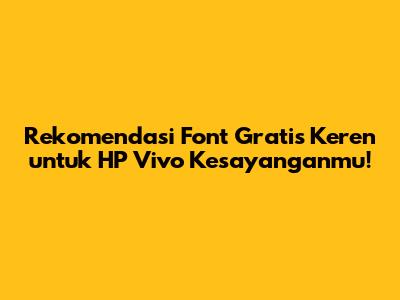
- Coba Berbagai Kombinasi: Jangan ragu untuk mencoba berbagai kombinasi font untuk menemukan tampilan yang paling cocok untuk HP kalian. Kalian bisa menggabungkan font yang berbeda untuk judul, subjudul, dan teks isi.
Hai guys! Siapa di sini yang suka banget gonta-ganti tampilan HP, khususnya font? Pasti seru banget ya rasanya kalau kita bisa mengubah-ubah font di HP Vivo kesayangan kita. Nah, buat kalian yang lagi nyari rekomendasi font gratis dan keren untuk HP Vivo, pas banget nih! Di artikel ini, kita bakal bahas tuntas tentang font-font kece yang bisa kalian unduh dan pasang secara gratis. Dijamin, tampilan HP kalian bakal makin stylish dan beda dari yang lain!
Kenapa Sih Kita Perlu Ganti Font di HP?
Sebelum kita masuk ke rekomendasi font, ada baiknya kita bahas dulu nih, kenapa sih kita perlu ganti font di HP. Selain untuk meningkatkan tampilan visual, ganti font juga bisa memberikan beberapa keuntungan lain, lho. Pertama, dengan mengganti font, kita bisa menyesuaikan tampilan HP sesuai dengan kepribadian dan selera kita. Misalnya, kalau kalian suka tampilan yang elegan, kalian bisa memilih font serif yang klasik. Atau, kalau kalian lebih suka tampilan yang kasual dan modern, kalian bisa memilih font sans-serif yang simpel.
Selain itu, ganti font juga bisa meningkatkan kenyamanan membaca. Beberapa font didesain khusus untuk memudahkan mata dalam membaca teks, terutama dalam jangka waktu yang lama. Ini sangat berguna, apalagi kalau kalian sering membaca artikel atau buku di HP. Dengan memilih font yang tepat, kalian bisa mengurangi kelelahan mata dan menikmati pengalaman membaca yang lebih baik. Gak cuma itu, mengganti font juga bisa bikin HP kita jadi lebih personal dan unik. Dengan memilih font yang sesuai dengan gaya hidup dan preferensi kita, kita bisa mengekspresikan diri melalui tampilan HP. Jadi, tunggu apa lagi? Yuk, mulai eksplorasi berbagai font keren dan sesuaikan tampilan HP Vivo kalian!
Rekomendasi Font Gratis Keren untuk HP Vivo
Nah, sekarang saatnya yang paling ditunggu-tunggu, yaitu rekomendasi font gratis yang bisa kalian gunakan di HP Vivo. Berikut adalah beberapa pilihan font keren yang bisa kalian coba:
1. Montserrat
Font Montserrat ini adalah font sans-serif yang sangat populer. Desainnya bersih, modern, dan mudah dibaca. Montserrat sangat cocok untuk tampilan yang minimalis dan elegan. Kalian bisa menggunakannya untuk berbagai keperluan, mulai dari tampilan antarmuka HP, pesan teks, hingga penulisan dokumen. Kelebihan lain dari Montserrat adalah ketersediaannya dalam berbagai variasi ketebalan (bold, italic, dll.), sehingga kalian bisa menyesuaikannya dengan kebutuhan.
2. Open Sans
Open Sans adalah font sans-serif lainnya yang sangat populer dan serbaguna. Font ini didesain oleh Steve Matteson dan telah menjadi salah satu font Google yang paling banyak digunakan. Open Sans sangat cocok untuk tampilan yang ramah dan mudah dibaca. Karakteristiknya yang netral membuat font ini cocok untuk berbagai jenis konten, mulai dari artikel berita hingga tampilan antarmuka aplikasi. Open Sans juga tersedia dalam berbagai variasi ketebalan, sehingga kalian bisa menyesuaikannya dengan kebutuhan.
3. Roboto
Roboto adalah font sans-serif yang dikembangkan oleh Google untuk sistem operasi Android. Font ini memiliki tampilan yang modern, bersih, dan mudah dibaca di layar. Roboto sangat cocok untuk tampilan antarmuka HP, termasuk menu, ikon, dan teks. Keunggulan lain dari Roboto adalah ketersediaannya dalam berbagai bahasa, sehingga kalian bisa menggunakannya di HP Vivo dengan berbagai pengaturan bahasa.